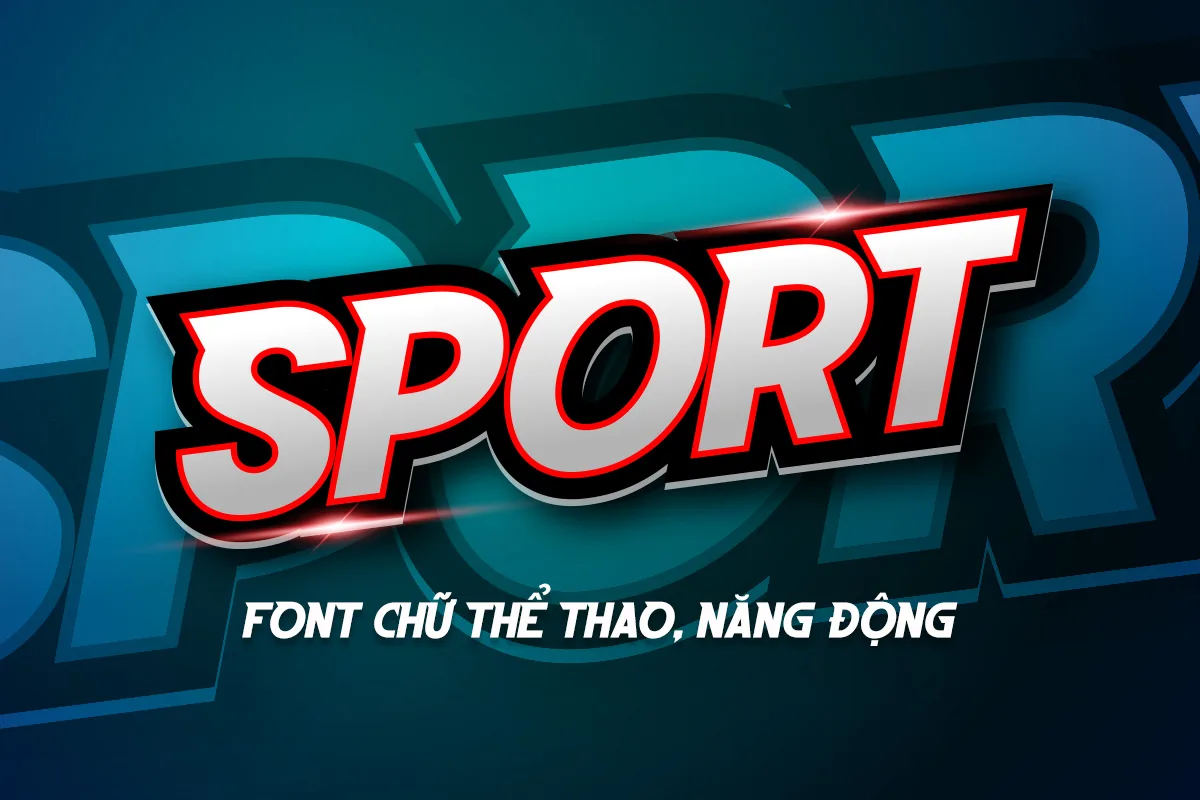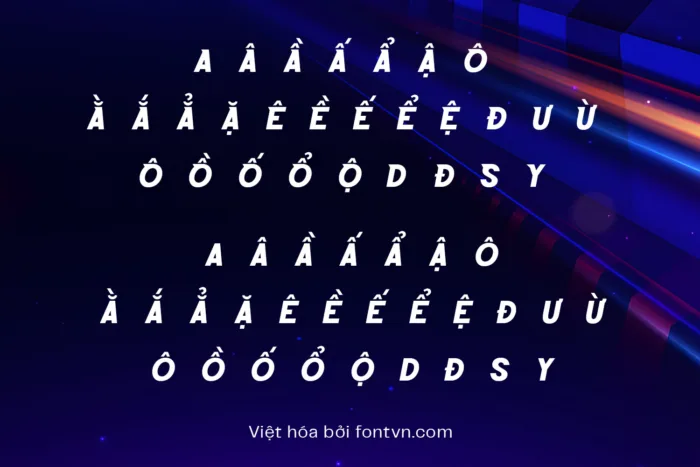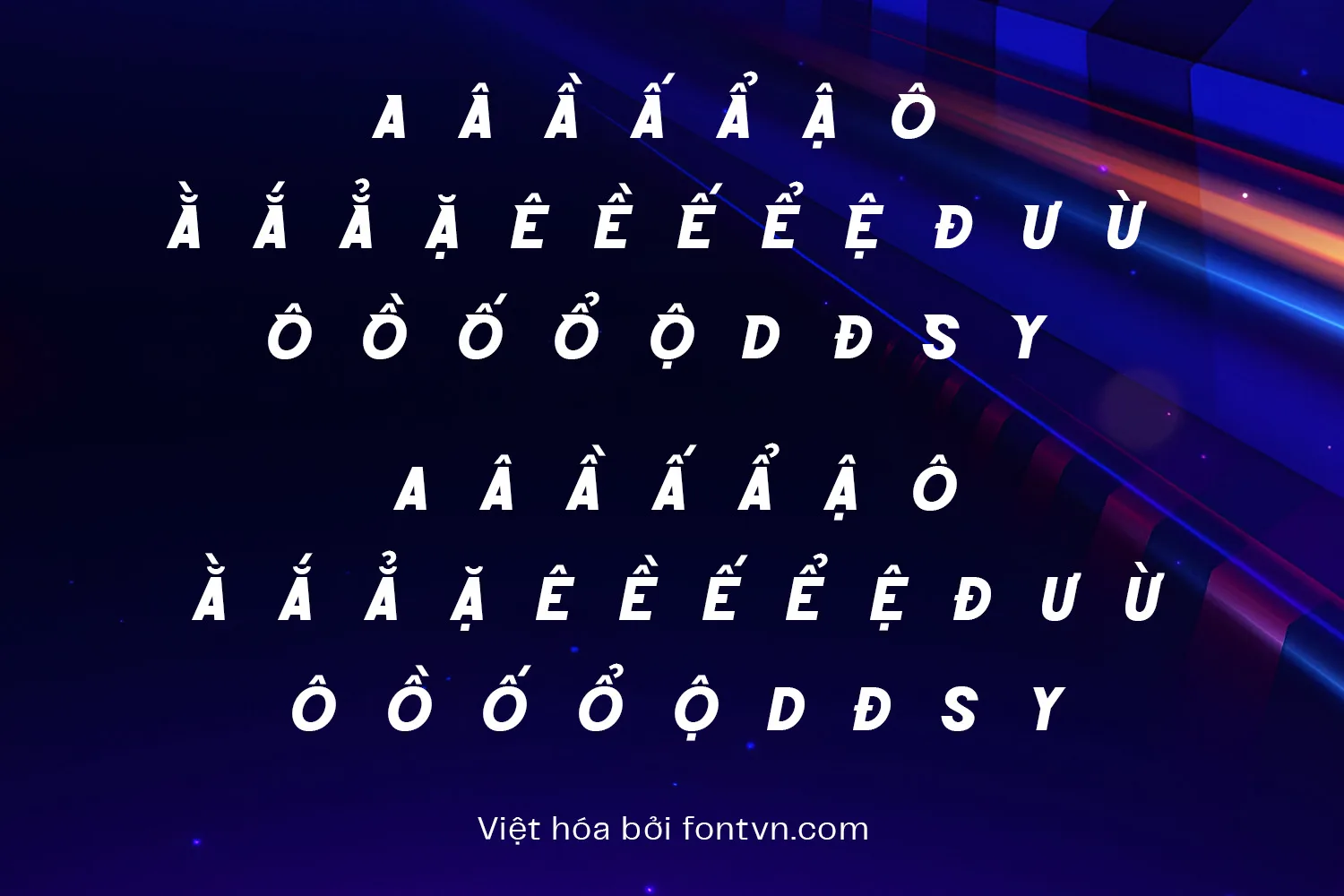
DVN SPEED Việt hóa – Font chữ thể thao và tốc độ
DVN SPEED Việt hóa là một kiểu chữ sans-serif đậm nét, thiết kế theo phong cách thể thao – tốc độ với các đường cắt sắc sảo, hình khối mạnh mẽ và cấu trúc chắc chắn. Font mang lại cảm giác bứt phá, quyết đoán – rất thích hợp dùng cho tiêu đề, poster sự kiện, logo đội tuyển hoặc game hành động.
Font không đi kèm hiệu ứng ánh sáng hay viền như trong ảnh minh họa – những hiệu ứng đó chỉ là thiết kế mô phỏng. Tuy vậy, DVN SPEED vẫn đủ sức tạo ấn tượng mạnh mẽ ngay cả khi sử dụng thuần túy nhờ form chữ khỏe khoắn và cá tính.
Bộ font đã được Việt hóa đầy đủ, hỗ trợ tốt tiếng Việt với dấu sắc nét và bố cục hợp lý.